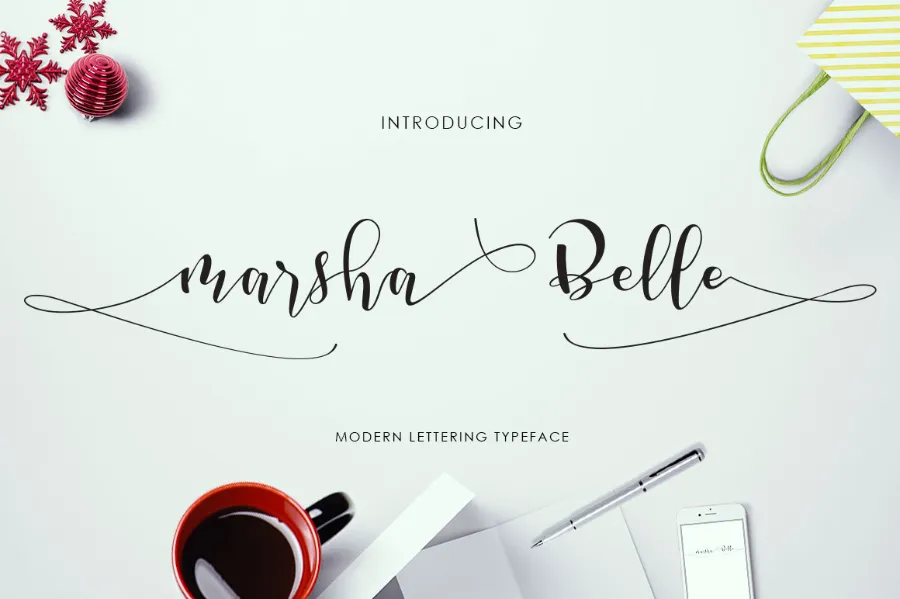
Na categoria de fonts para escrita a mão, está disponível uma nova opção chamada Marsha Belle Script Font, perfeitamente criada pelo designer Hamilton. Esta elegante e moderna tipografia foi projetada para se adaptar a diversos tipos de conteúdos gráficos, incluindo logomarcas, cartões de convite de casamento, postais, embalagens, roupas, flyers, revistas, panfletos, cabeçalhos, assinaturas, etiquetas e até mesmo anúncios. Este belo font é especialmente útil para criar um design único e atraente em uma variedade de materiais impressos. Marsha Belle Script foi projetado para trazer leveza e movimento às suas criações, com linhas suaves que flutuam ao longo do baseline padrão. Esta elegante tipografia é perfeita tanto para textos como para gráficos em preto e branco ou cores vibrantes. Para designers de todos os níveis, este font oferece uma grande flexibilidade para se adaptar a diferentes tamanhos de texto e estilos. Seja você um designer de nível básico ou profissional, com Marsha Belle Script Font, você pode alcançar um novo patamar em sua habilidade visual e criativa.